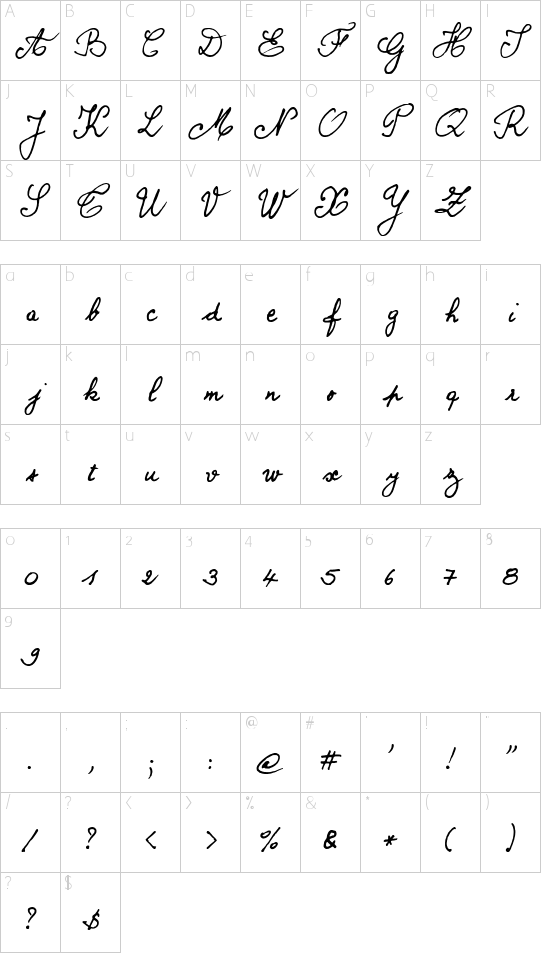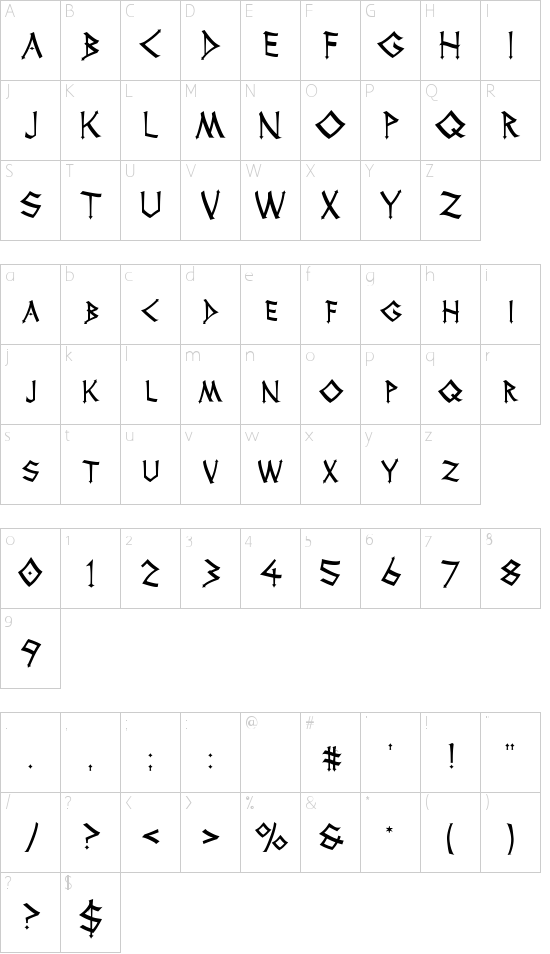
82 Tattoo Schriftarten Altdeutsch Schrift Tattoo
Wenn du die altdeutsche schrift für tattoos bevorzugst kannst du sie nicht nur für namen sondern auch für sprüche und metaphern verwenden. Best tattoo of the day 2013 betende hände mit rosenkranz.
44 Epische Tatowierung Schriftarten
Tattoo schriftarten altdeutsch schrift tattoo. 19 08 2018 erkunde norbs pinnwand tattoos mit schrift auf pinterest. Altdeutsche schrift tattoo schriften altdeutsche schrift.
Arabische schrift older posts. Laden sie 103 tätowierung schriftarten herunter. Tattoo schriftarten können verwendet werden um sich eine vorschau für textbasierte tätowierungen zu erstellen und so einfacher über diese zu entscheiden.
Die altdeutsche schrift beschränkt sich nicht nur auf eine schriftart sondern hat verschiedene geschichten und ursprünge. 08 08 2020 erkunde aleksej feers pinnwand tattoo schrift alphabet auf pinterest. Weitere ideen zu buchstaben schriftarten alphabet buchstaben schriften alphabet.
Durch den kontext dieser schrift und den gedanken in vielen köpfen wird die altdeutsche schrift leider oftmals mit rechtsradikalem gedankengut in verbindung gebracht. Durch den kontext dieser schrift und den gedanken in vielen oköpfen wird die altdeutsche schrift leider oftmals mit rechtsradikalem gedankengut in verbindung gebracht. Auch deutsche fonts asiatische fonts sowie alle speziellen schriften wie altdeutsche schriften tatto schriftarten schriften f r word chinesische schrift und vieles mehr.
Affection betende hände mit rosenkranz best tattoo of the day 2013. 19th alchemy tattoo expo conthey scheiz. Reine text tattoos liegen heute immer mehr im trend und immer mehr menschen wählen worte namen kurze zitate oder bedeutsame redewendungen um sich durch ihre tattoos auszudrücken.